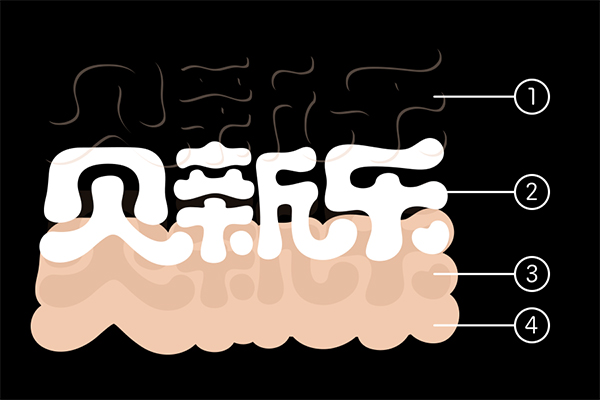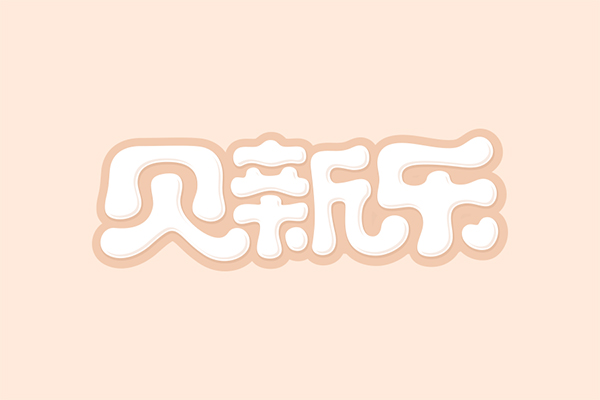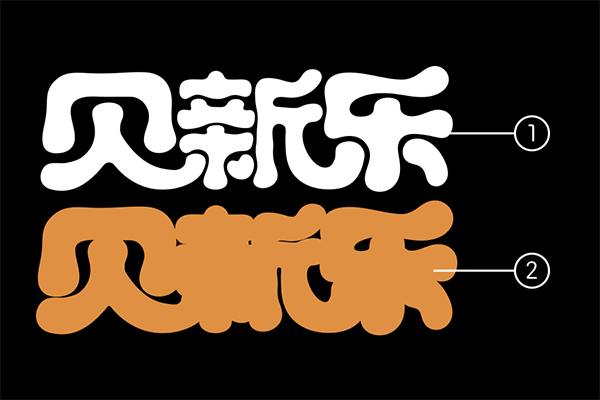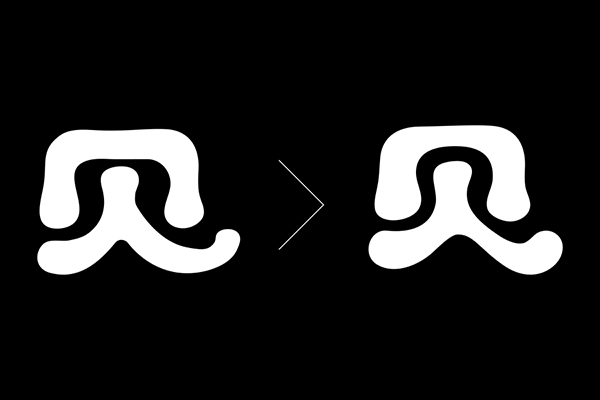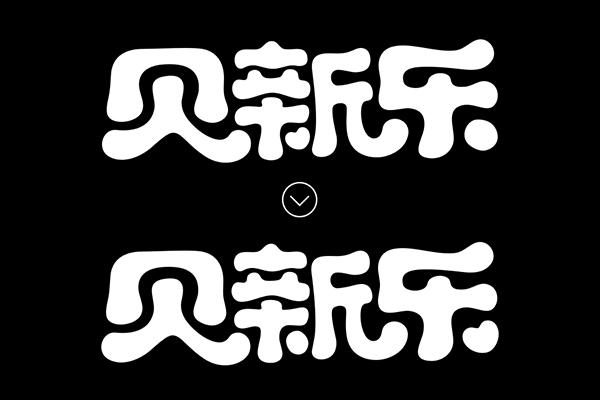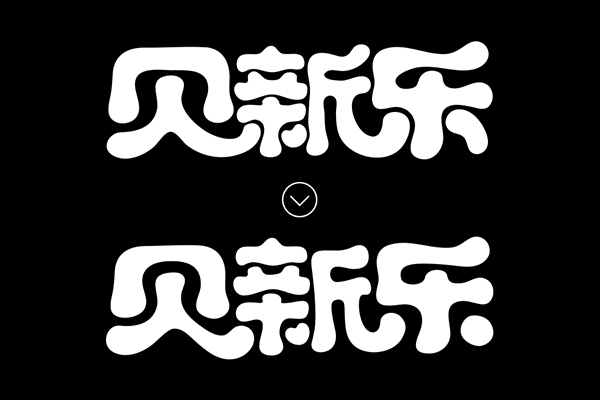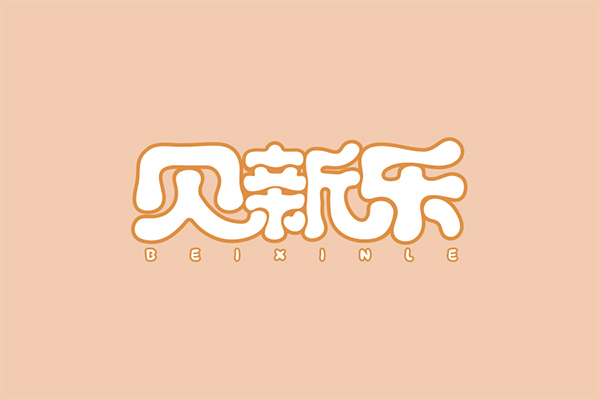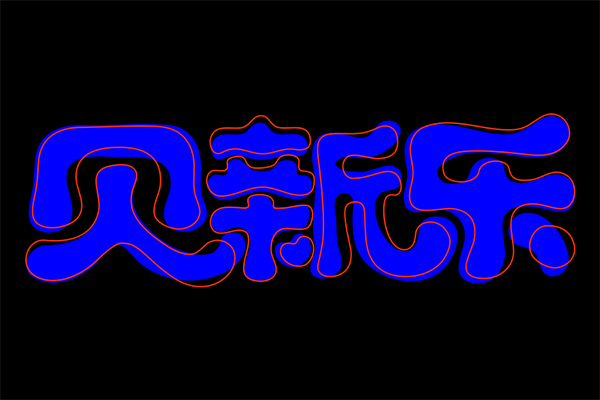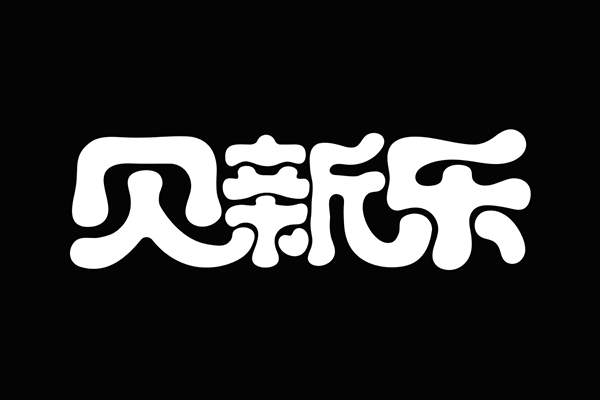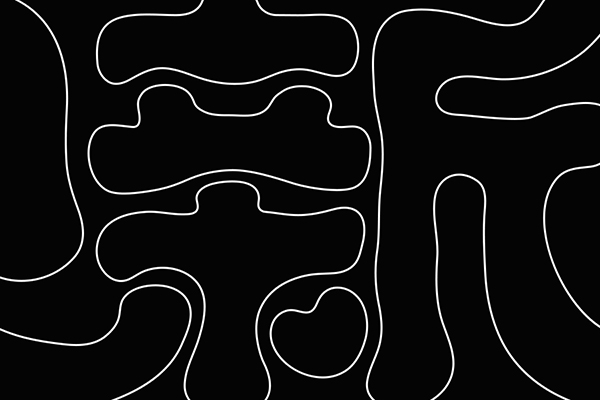
前言:改字就像是一个半命题作文,材料给到了我会尽量叙事好。帮大家改字不是全部推翻重来,这样没有太大意义,我会尽量维持原有字体方向,解决主要矛盾,帮大家理清思路,并拓展一些小知识点。如果觉得改字中有不妥之处,欢迎留言讨论。
每一期我会选择比较有代表性的字进行修改,未被选用的投稿莫怪,望下期有你。本期选的字是一组卡通类型,该类字多应用于儿童、母婴产品,主要特点是轻松有趣亲和力十足。
如何通过字体设计表达儿童化的气质呢?原稿字已经给出了不错的答案:柔和圆润又多变的笔画。所以轻松愉悦的感觉我们便很直观的在这组字中获取,配合字体中笔画的连笔共用、描边的处理使之整体性更佳。
抓住了上述特征你一定会得到一组看起来还挺有卡通范的字,但是有些问题是不能回避的,因为他会让你的字变的更精致。
我们往往注意了笔画、细节的统一,空间的统一最容易被忽视。先去掉原有的描边留下字体“真身”并作反白处理,便于观察字体的负空间。
如果以第一个字的空间作为标准的话,后面两个字是有些偏紧的,尤其是‘亲’这个局部,笔画较多,空间尤为局促。
再看笔画的轮廓线,有一些没有必要的“抖动”如“斤”第二笔,这样的变化就会显得细碎;另外一些线条柔和但不够流畅,这其实就比较好修改了,只需调整锚点手柄即可。
说到锚点想插播一条注意事项,锚点一定不是越多越好,很多无用的锚点有时会破坏线条的流畅性,而且自己调节起来也会比较麻烦。所以,在调节这组字之前我会执行【对象-路径-简化】选项。
空间的均衡与线条的流畅这是接下来调整的方向。如上图,大家可以观察“贝”字内部空间变化和笔画线条的调整。
再上一张初次调整前后对比,红色线条为调整后的轮廓。整体的节奏保持不变,上面强调的空间统一,在本组字中的调整可以简单理解为空间大的缩小点,空间挤的加大笔画间距。
大家应该早就注意到了“新”字中一点用到了图形爱心,很不错的招式,但是总觉得这个心的位置有些尴尬,或者说塞到犄角旮旯里过于低调了,索性与“乐”子最后一笔对调位置,视觉上会凸显一些。
修改这种类型的字只需注意上述所说,剩下的就是多点耐心和时间调整锚点手柄。
上图是原稿字的层次,一共是两级,看起来像是简单的加了个描边的效果,也不能说这样做不对,只是可以表现的更丰富点,如下图调整。
只是多增加了两级,第一级的高光和第三级的小投影,四级的层次当然不是居中对齐,一定是有错位关系,比如本组字假设光从左上角照过来,放大细节如下图。
# 终稿对比
最后在总结一下,卡通字的设计尤其关键的是笔画的柔和圆润,再者注意空间的均衡与统一,最后层级关系要明确要到位,下面再瞅一眼修改前后的对比吧。